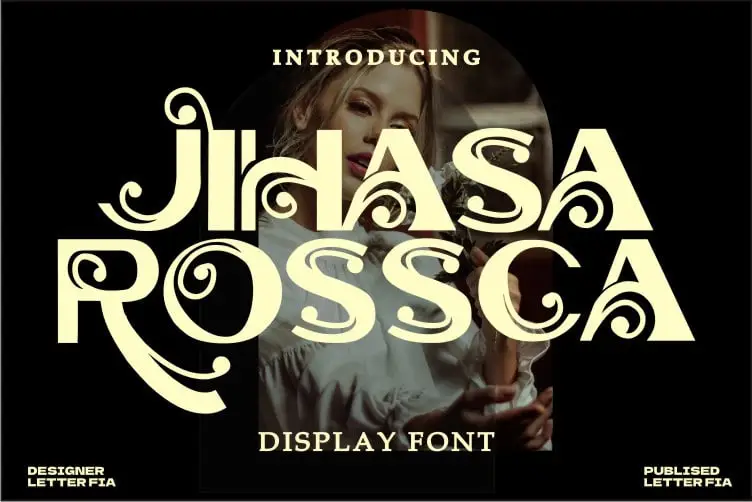
Jihasa Rossca Font – Download Grátis
A fonte Jihasa Rossc é uma bela escolha para qualquer projeto que busque arredondar a experiência visual com um toque vintage e único. Este font é cuidadosamente projetado, repleto de detalhes meticulosos que tornam cada característica realçada e interessante. Seja você criando arte gráfica digital ou trabalhando em uma publicação impressa antiga, Jihasa Rossc terá a capacidade de adicionar um toque especial à sua criação. Não apenas é elegante na aparência, mas também tem o potencial de transformar qualquer projeto, seja ele digital ou impresso. Ideal tanto para iniciantes quanto para profissionais experientes, esta fonte Jihasa Rossc oferece uma maneira versátil e autêntica de dar vida a seus projetos. Não hesite em adicioná-la ao seu arsenal de fontes vintage da sua biblioteca pessoal.